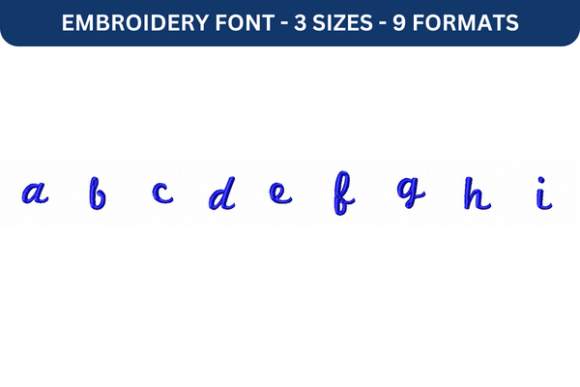
Marketing Script Font Lower a to I
Om du letar efter högkvalitativa tillgångar som Marketing Script Font Lower a to I, är detta premiumpaket ett fantastiskt val för dina kreativa projekt.
Oavsett om du skapar POD-produkter (Print on Demand), bröllopsinbjudningar eller grafik för sociala medier, är Marketing Script Font Lower a to I ett perfekt val.